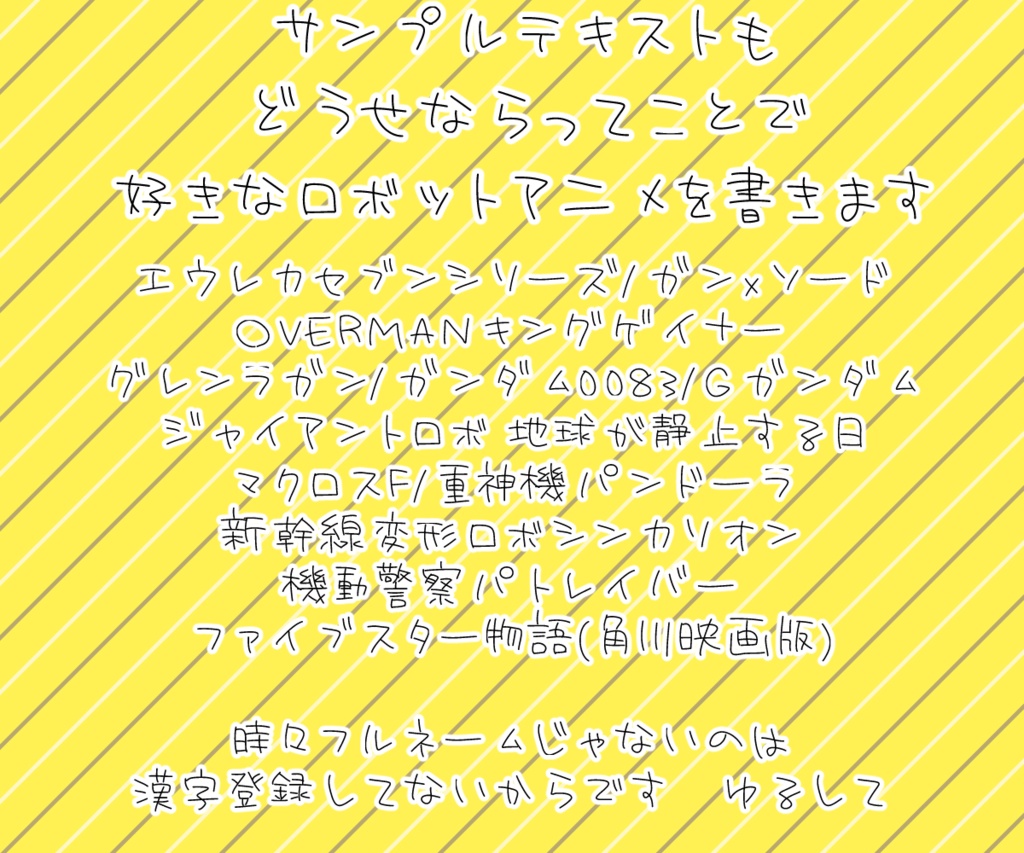
お布施版手書きフォント「おむらいすフォント」
※こちらは「お布施版」です。 れいざに金を払いたい・れいざに何かをおごりたい・おむらいすフォントが好きすぎるなど、「お金を払ってもOK!」という人向けです。フォントの内容は同一なのでご注意ください。 れいざが書いたオリジナルフリーフォントです。『「お」と「む」一緒やん』と言われたので作りました。 手書き感が欲しい時に使ってみてください。 【以下はファイル内の「Readme」と同一の文章です】 収録文字:ひらがな/カタカナ/アルファベット/一部記号/教育漢字(小学1年生~6年生までの漢字) 個人・商用問わず、ご自身の作品(イラスト/同人誌/ゲーム/webページ/ライブ配信など)に無料でお使いいただけます。 クレジット・使用報告などの条件はございませんが、使用した際に記載・報告いただけると自分が喜びます。 【注意点】 ・このフォントの著作権はれいざにあります。著作権は放棄していません。 ・フォントファイル本体の二次配布、加工、販売は禁止しています。画像加工への制限はございません。 ・フォントに関してのサポートには一切応じられません。申し訳ございません。 ・このフォントを使用したことによるトラブル、不利益には一切の責任を負いません。 その他、何かありましたらTwitterアカウント(@Reiza_walfisch)までご一報ください。